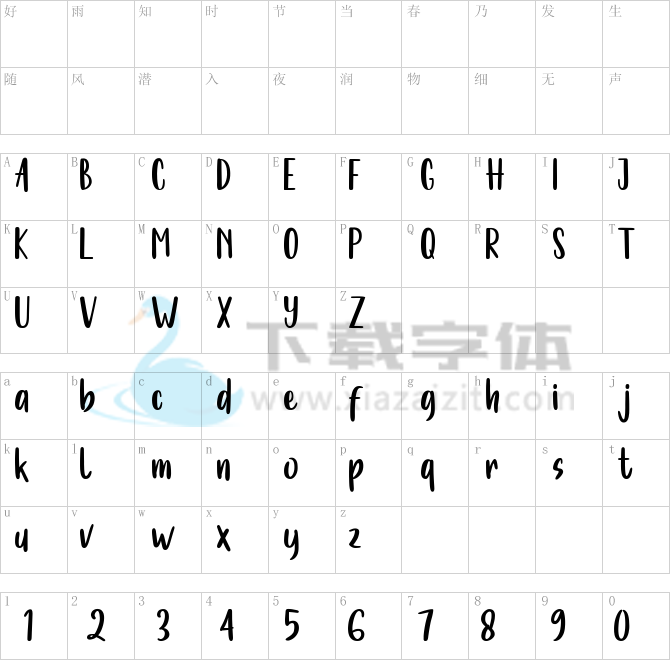
Autumn Stories.ttf字体下载
Autumn Stories.ttf字体下载,这款字体结构工整、笔画清晰,兼顾美观与易读性,适用于标题、正文、海报、包装、LOGO 等多种场景。字形优雅稳定,风格百搭耐看,适配日常排版与创意设计,让文字呈现更舒适、更具质感。Autumn Stories.ttf字体下载一笔一画,皆是细节,以均衡的比例、流畅的线条打造舒适视觉体验,字形端正大气,风格简约现代。无论是商业设计、品牌宣传还是日常排版,都能轻松驾驭,让文字更有格调与力量。Autumn Stories.ttf字体下载字体下载。